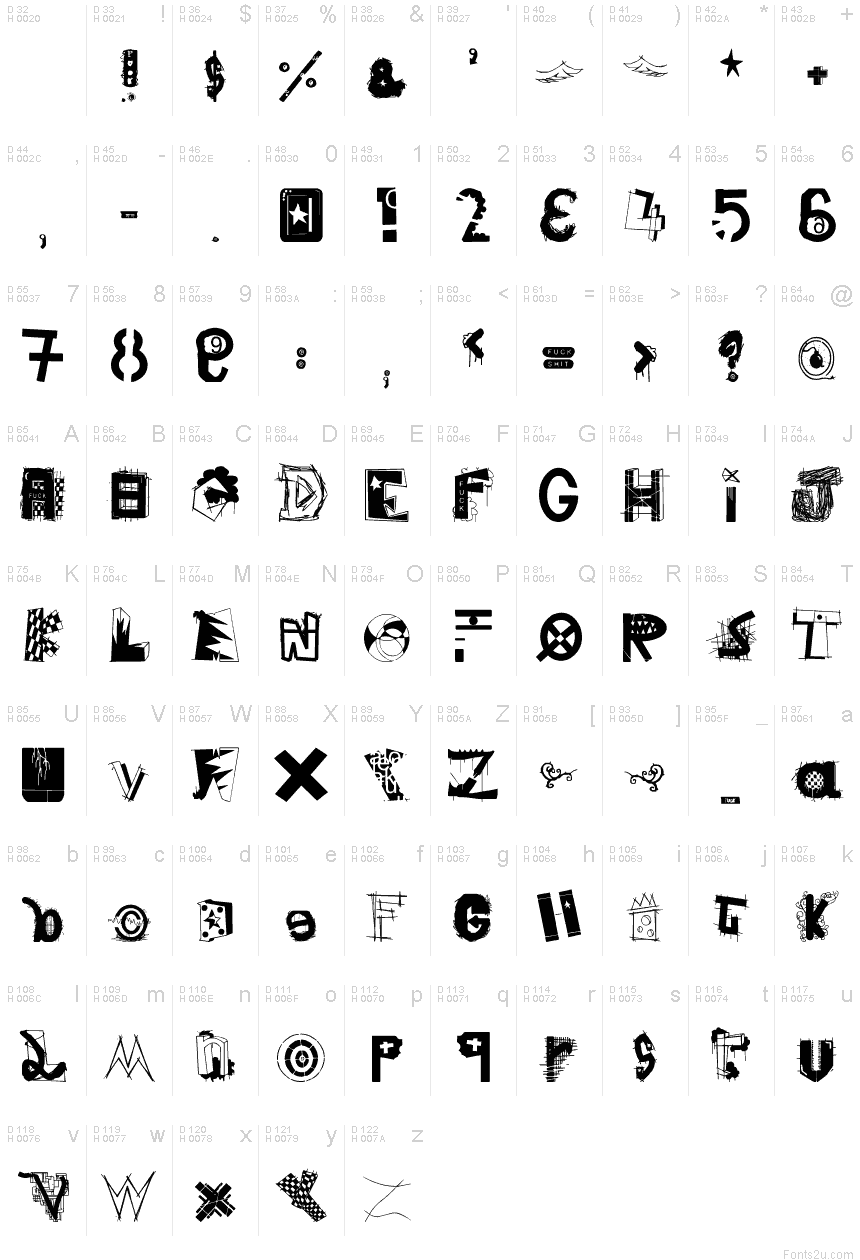
Tom to darmowy, ręcznie tworzony krój dekoracyjny o surowym, kolażowym charakterze. Litery łączą w sobie kleksy tuszu, szkicowe linie, segmentową geometrię i ostre kąty, dzięki czemu krój sprawia wrażenie zbioru grafik, a nie dopracowanego, jednolitego projektu.
To sprawia, że naturalnie sprawdza się w nagłówkach plakatów, okładkach zinów, oprawie graficznej zespołów, odzieży streetwearowej i planszach tytułowych, gdzie darmowy font ma samodzielnie nadać projektowi niezależny, artystyczny klimat. Używaj go do krótkich słów, inicjałów czy monogramów – zmienne motywy sprawiają, że nawet kilka liter nabiera wyrazistości.